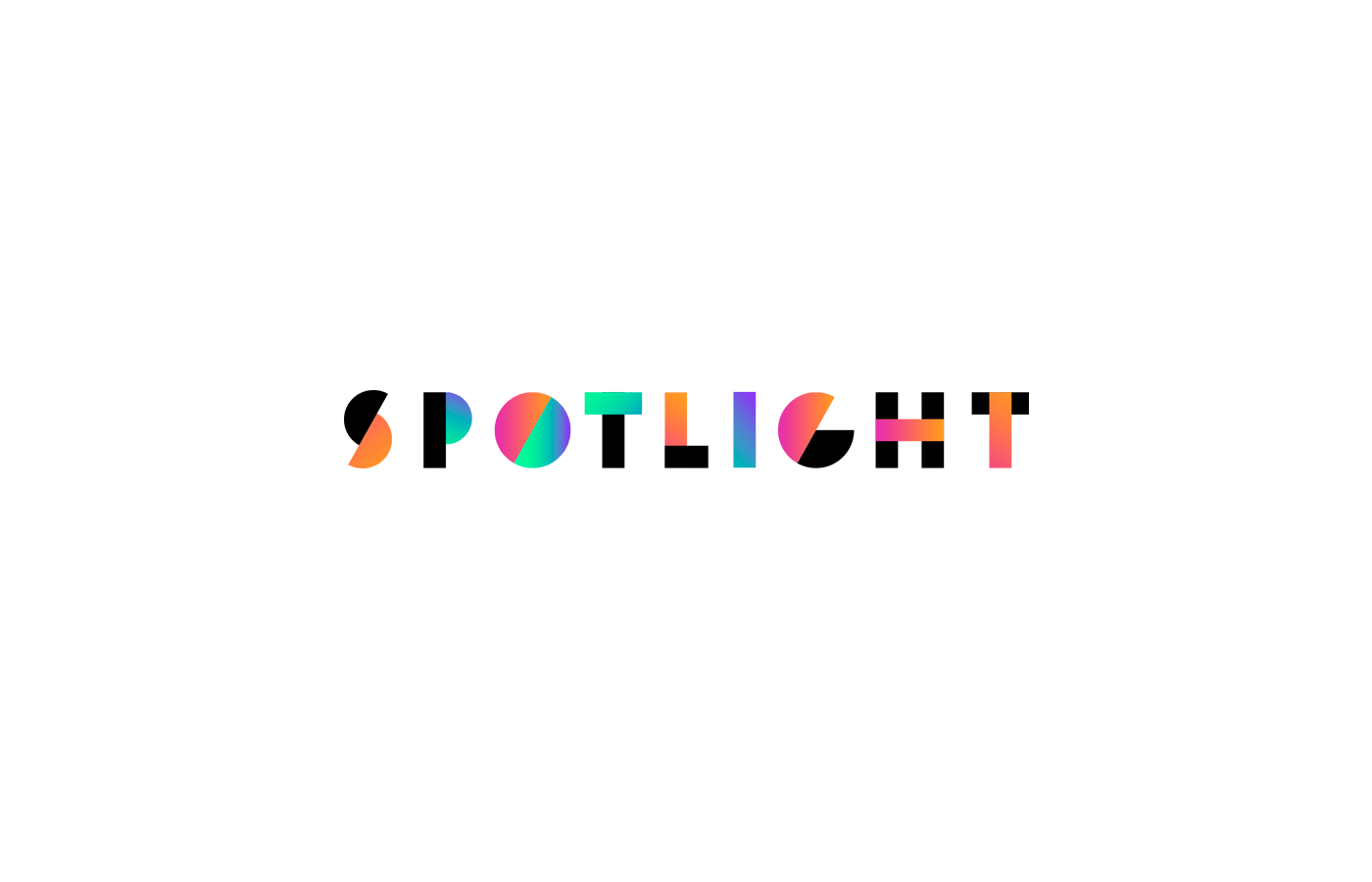
Helsinki Spotlight Festival Schrift gesucht
ich suche die Schriftart vom Helsinki Spotlight Festival, zu finden hier: http://the-manitou.com/spotlight.
Genauer gesagt, die Schriftart von Schriftzug "Spotlight" --> siehe Anhang.
Hallo @michael_jellbauer, die für das Festival und auf der von dir verlinkten Seite verwendete Schriftart ist die Futura PT.
Die Logotype ist derselben Seite zufolge, wenn man der farbigen Konstruktionsdarstellung glauben darf, eigens gezeichnet und basiert nicht auf einer verfügbaren Satzschrift.